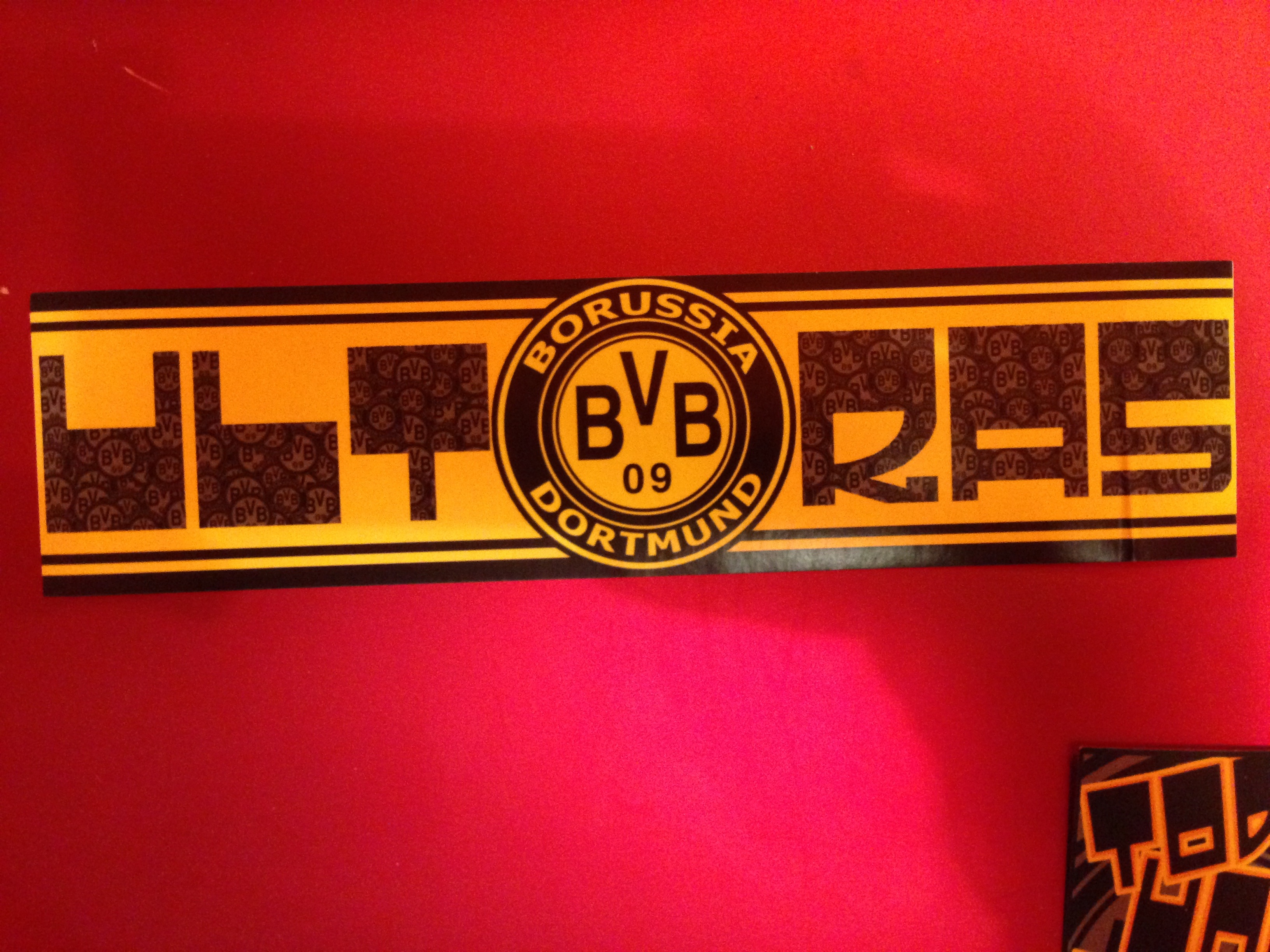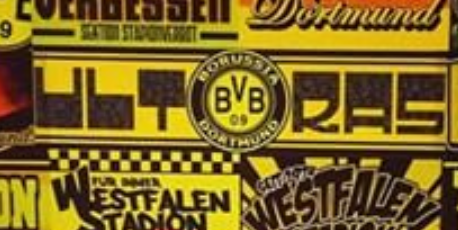
Suche ULTRAS-Schriftart
Ich hasse Dortmund selber wie die Pest, mich interessiert nur die Schriftart, also wäre ne konstruktive Antwort super.
Habe leider in der Suche nichts gefunden, wie gesagt ne konstruktive Antwort wäre wirklich super, da ich die Schrift zügig benötige.
ja, hatten wir schonmal.
die schrift scheint in ultra-kreisen recht beliebt zu sein und erinnert an die italienischen futurismus / avantgarde.
über die jetzige verwendung in den stadions dieser welt könnte man sicher eine diplomarbeit schreiben.
achso, mir gings eher um den stil mit dem charakteristischen ecken (siehe R).
die meisten ultras malen ihre transparente ja mit der hand und wandeln diese schriften ab.
was sehen wir denn auf dem bild, fanschals?
Das ist wohl ein Aufkleber …
Wenn ich mir die rechte untere Ecke des S anschau (ich hab jetzt bewusst nicht Rundung geschrieben) und auch den Bogen beim R, sieht das sehr handgemacht und nicht nach einer existierenden  Schrift aus. Die paar Buchstaben sind auch schnell im Illustrator, Corel etc. gezeichnet.